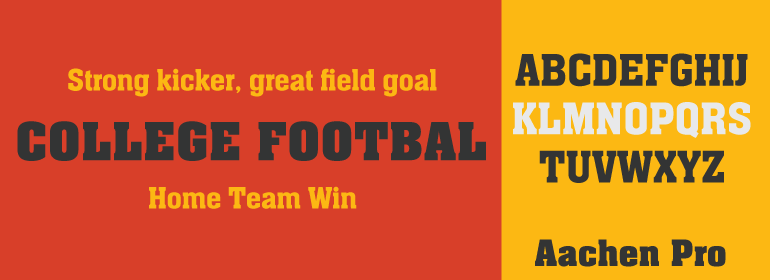
Aachen™
Aachen Bold由Colin Brignall于1969年设计。Aachen Bold是一款特粗体,字怀很窄,衬线又粗又短。它的粗度暗示着力量,能够满足注重视觉冲击的突出信息力量的情况。作为一款显示字体,建议该款字体在用于标题或者广告中的大小应该超过24pt。
Aachen Bold was designed by Colin Brignall in 1969. Aachen Bold is an extra bold typeface with very narrow counters and short slab serifs. Its boldness suggests power and will correspond to solid messages where visual impact is important. As a display type, this face is recommended for use over 24 point for titles, headlines or advertisements.